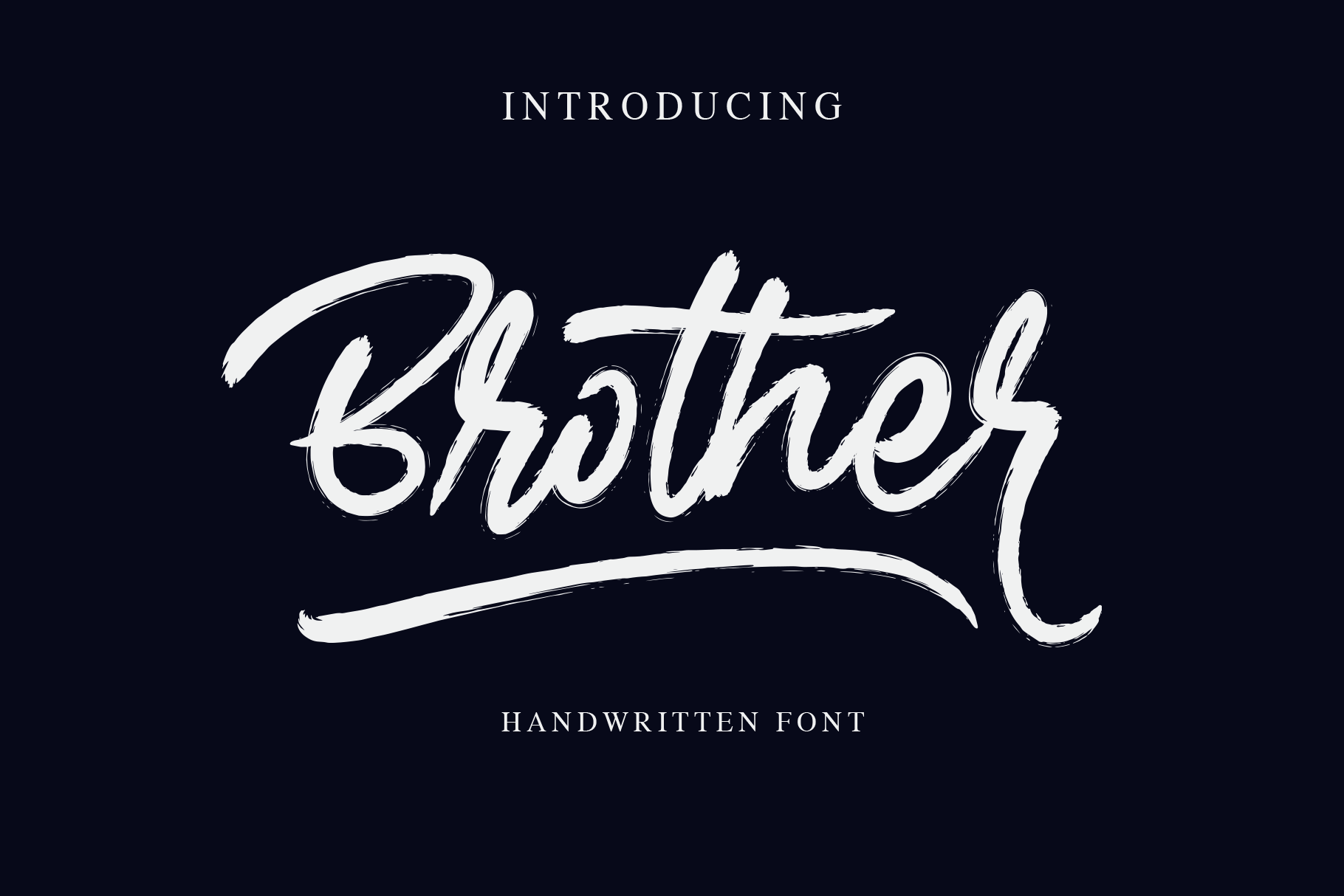
Brother Brush Font – Download Grátis
A M.0Type introduziu a Brother Font, uma script font elegante com toque de escrita à mão que é perfeitamente adaptada para várias tarefas gráficas. Quando tudo parece estático, aparece ela, um novo modelo cheio de interesse e ideal para projetos criativos como água-marinha em fotografias, capas de álbum, cartões de negócio, e muitos outros projetos de design. A Brother Font é a solução perfeita para dar um toque especial aos seus trabalhos. Ela traz uma brisa de originalidade à sua arte digital, garantindo que todos vejam seu trabalho como único e inspirador. Seja para um projeto pessoal ou profissional, a Brother Font oferece o acabamento sofisticado e elegante necessários para destacar suas criações no mundo do design moderno.